“字库”一词*早出自宋代的“字库塔”,中国传统文化中推崇“敬天惜字”。在仓颉造字便出现“天雨栗、鬼夜哭”、“龙乃潜藏”等奇观,文字紧密联系着天地,是先人的心迹,因此古人为焚烧字纸制定专门的礼仪和设施,字库塔即为焚烧字纸时所用的塔型小建筑。
20世纪80年代,步入数字时代,激光排照、计算机字库、电脑排版技术逐渐取代传统铅字印刷;20世纪90年代,中国计算机字库行业经历了高速发展的阶段。
但进入21世纪以后,市场接受互联网浪潮的数次洗礼,免费成为了网络繁荣背后的真正王道,由技术带来的免费便利与盗版猖獗不可遏制,整个字库行业发展遭遇空前冷冰。
2010年之后,随着互联网用户规模的不断壮大、用户付费意识逐渐提高、数字阅读的加速渗透以及版权环境的改善,字库行业逐渐复苏。
字库企业经营活动以字体、字库为核心
在字库行业中,企业的经营活动以字体、字库为核心。
字体是文字的外在形式特征,是某一类特定的文字之风格样式,是文化的载体。字体文化是传统文化的重要组成部分,汉字字体独特的方块字形包含着丰富的文化内涵和审美意蕴,是中华民族智慧的结晶。字库本身外在表现形式为“单字”,实质是为了得到可在计算机及相关电子设备的输出装置中显示相关字体字型而制作的由计算机执行的代码化指令序列,属于计算机程序。
计算机字库的开发,通常需要经过设计概念、设计种子字、拼字/修字、(符号+西文)设计、编程合库、品质检测、应用测试等步骤。
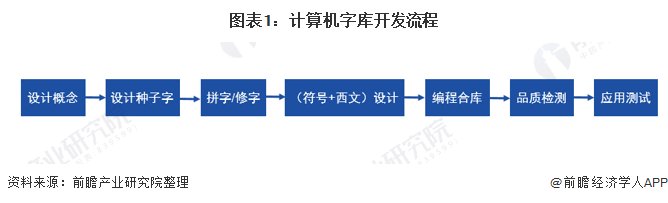
国内数字化阅读加速渗透
随着互联网和阅读技术的发展,依托手机、电子阅读器、Pad等设备进行的数字化阅读也在不断发展。第十七次全国国民阅读调查显示,2019年我国成年国民数字化阅读方式(网络在线阅读、手机阅读、电子阅读器阅读、Pad阅读等)的接触率为79.3%,较2018年上升了3.1个百分点。
根据中国音像与数字出版协会发布的《2019年度中国数字阅读白皮书》,截至2019年,中国数字阅读用户总量达到4.7亿,人均纸质书接触量8.8本,人均电子书接触量14.6本,其中接触20本以上电子书占比53.8%,较2018年上涨3.4%。
国内版权环境持续改善
根据国家知识产权局发布的《2019年中国知识产权保护状况》,2019年知识产权保护社会满意度达到78.98分(百分制),较2018年提升2.1分,权利人满意度升值新高,达到79.89分。
除此之外,中国欧盟商会发布的《商业信心调查2019》报告显示,约六成企业认为中国知识产权行政与司法保护力度明显加强;世界知识产权组织称赞中国在知识产权保护领域取得巨大进步,中国声音正在成为包括知识产权保护体系在内的全球政策体系的重要声音。
字库行业市场规模不断增长 方正、汉仪占据大部分市场份额
2019年中国字库行业市场规模已经达到8亿元左右,未来随着国内版权市场的进一步改善以及字库行业B端和C端业务的持续拓展,字库行业市场规模将进一步增长,预计2023年中国字库行业市场规模将超过16亿元。
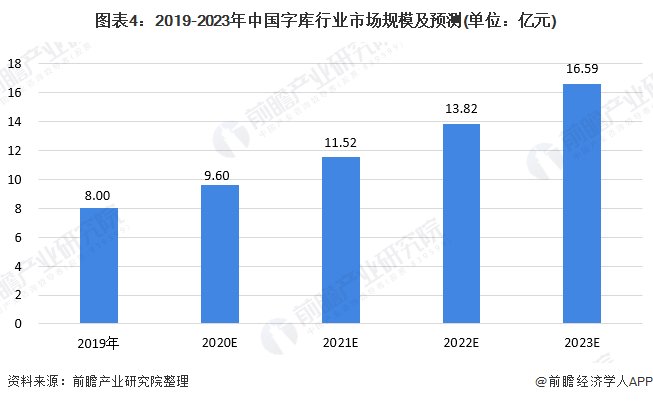
在国内市场,目前行业内较为知名的字库设计生产企业有方正、汉仪、华康、文鼎、华文等。同时,在字库行业市场需求不断扩大及大众审美多样性快速发展的背景下,各类新兴中小型字库工作室逐渐发展起来,如造字工坊、字体视界等。
方正、汉仪作为两家老牌字库厂商,拥有内容、技术、人才、品牌、资金等方面的优势,占据着国内字库市场的大部分份额。